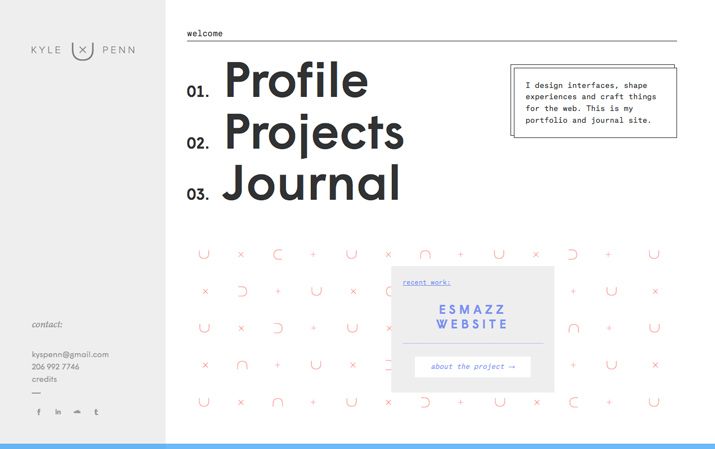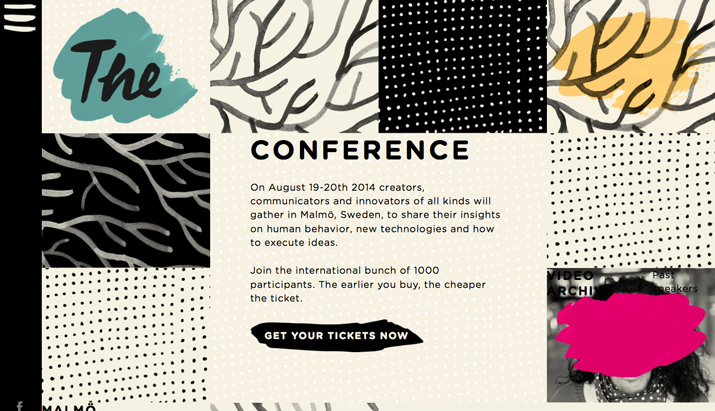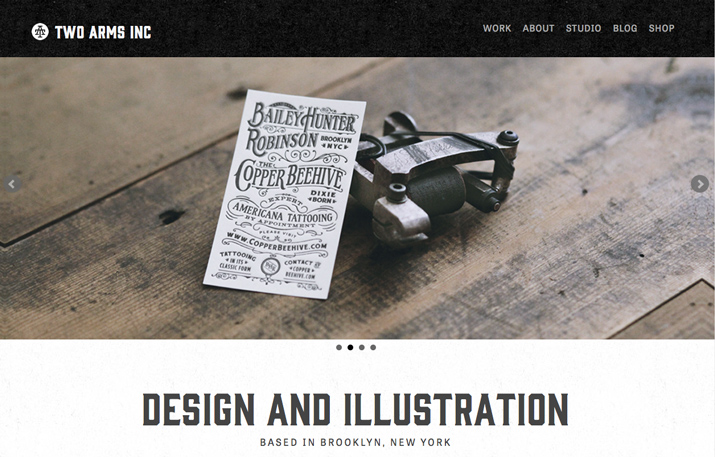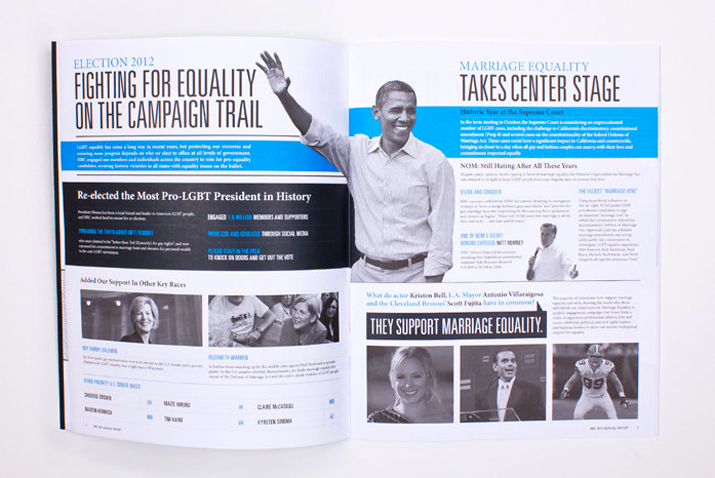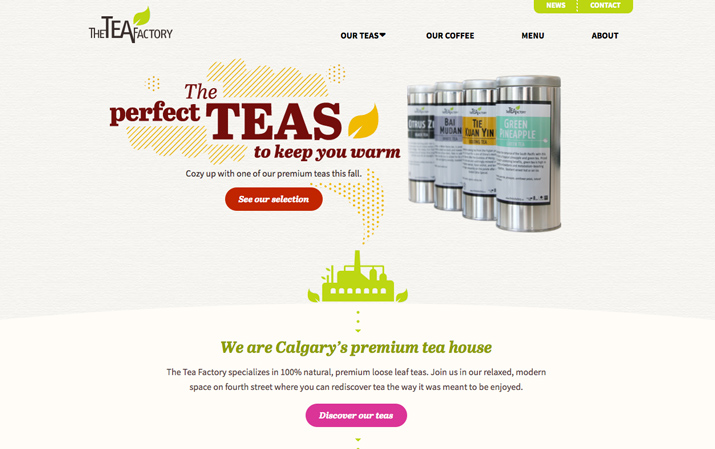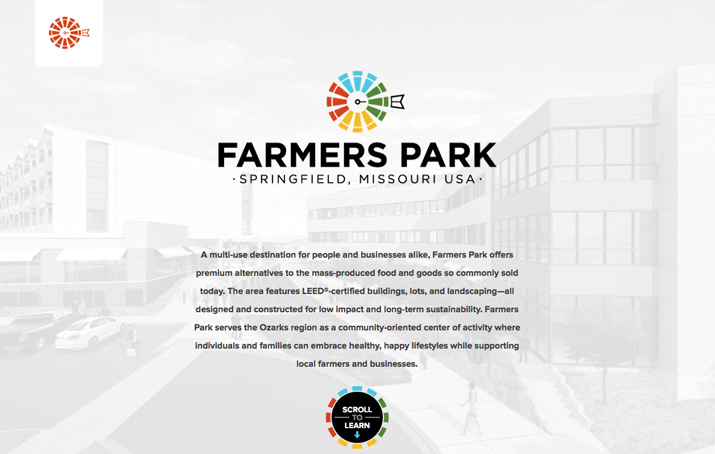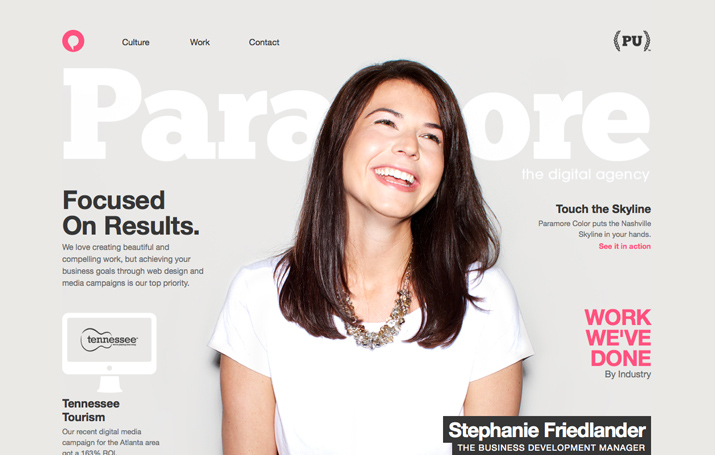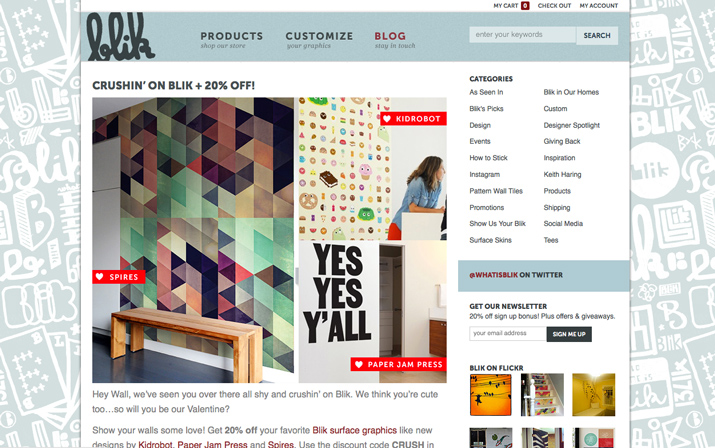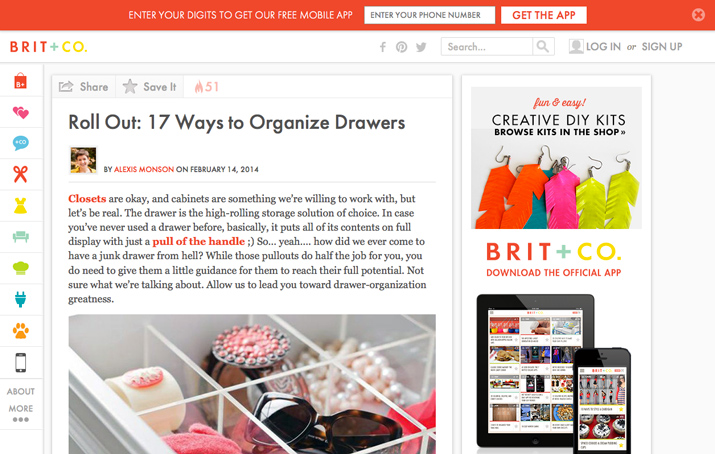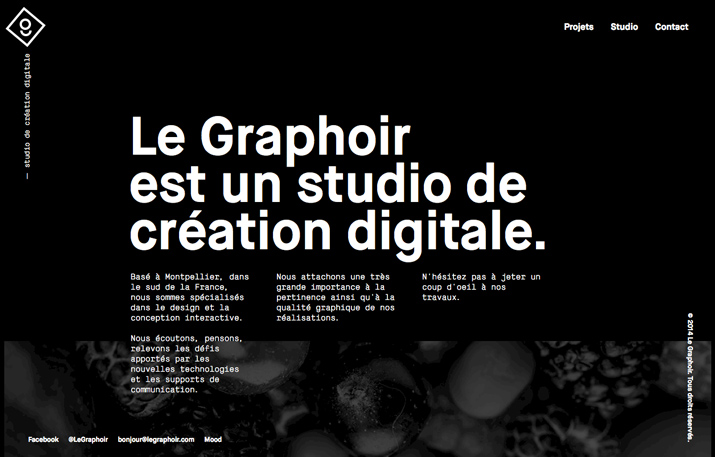
Diseño web: Crea jerarquía visual en tus páginas web usando tipografía
La jerarquía visual es un elemento visual importante en cualquier proyecto de diseño web. Dice a las personas dónde mirar y qué cosas en la pantalla o material impreso son las más importantes. La jerarquía da a los lectores un sentido de cómo leer material, desde el inicio hasta el final, usando pistas visuales.
Aunque puedes crear jerarquía visual usando diferentes herramientas, hoy veremos formas de crear estructuras solo usando tipografía.
Por qué la jerarquía es importante
La jerarquía de fuentes organiza y da orden a los elementos de texto en tu diseño web. Al igual que los desarrolladores y diseñadores web usan etiquetas para encabezados h1, h2 y h3, entre otros para organizar la importancia del texto, la jerarquía visual usa pistas visuales. Además, la jerarquía visual ayuda al lector a escanear el texto, leyendo pedazos de textos de forma más rápida en piezas que lucen similar.
Por lo general, los lectores occidentales empiezan de la parte superior izquierda y hacia la derecha y luego hacia abajo. Las letras están organizadas para imitar este comportamiento. Sin embargo, ¿qué sucede cuando el texto más grande y en negrita se encuentra a mitad de la página web? Generalmente, el lector empezaría por ahí y luego iría la parte superior y continuar con la lectura normal.
La jerarquía es importante porque permite que el diseñador determine lo que alguien leerá primero, segundo y así sucesivamente. Debido a esto, el diseñador puede crear fuentes de una forma en que él o ella sepa qué información puede ser recibida y en qué orden.
Crear jerarquía es importante para los diseñadores, pero estoy es igual de importante para los lectores. Una jerarquía visual buena nos dice lo que es importante porque facilita la lectura. Por ejemplo, sabes que el encabezado es lo más importante (o lo que llama la atención) de la historia porque es lo más grande, seguido de los subencabezados y luego el cuerpo del texto. Para propósitos de legibilidad, puedes leer el texto grande y tener una idea si el artículo será interesantes antes de invertir mucho tiempo en el contenido.
Cómo crear jerarquía
No existe una solución simple para crear jerarquía visual usando texto. Esto puede crearse con tamaño, peso, color, textura, opciones de fuentes y combinaciones, orientación y espacio o una combinación es todo lo mencionado.
Tamaño
Una de las formas más sencillas de establecer jerarquía con tipografía es a través del tamaño. Los lectores, con frecuencia, ver la tipografía más grande primero y empiezan a leer desde ahí.
Con relación al tamaño, la escala es muy importante. Para crear una jerarquía diferente, los tamaños deben tener una variación diferente en relación con las otras fuentes de la página. Lo que debes considerar es que las diferentes fuentes crean escalas diferentes. así que cambiar el tamaño de punto puede no ser diferente; necesitas mirar cómo las fuentes funcionan juntas para asegurar el tamaño y escala apropiados.
Entonces, ¿cómo empiezas a crear el tamaño y escala adecuados para un proyecto? Empieza con el texto principal y parte desde ahí. En cuanto a elementos de texto que son usados para llamar la atención, sé atrevido:
Aquí tienes algunos porcentajes que pueden ayudarte:
- Texto principal (14 puntos)
- Encabezados principales 250 % más que el cuerpo de texto (35 puntos)
- Encabezados secundarios: 175 % más que el cuerpo de texto (25 puntos)
- Elementos de navegación: 165 % más que el cuerpo de texto (25 puntos)
- Menú o menús secundarios: 140 % más que el cuerpo de texto (20 puntos)
Fuentes
Después del tamaño, las fuentes son el elementos más usado en términos de creación de jerarquía tipográfica. La clave es tener contraste entre las fuentes. Esta es la razón por qué los diseñadores seleccionan una fuente serif y otra sans serif para un proyecto.
Para tener las mejores combinaciones, busca fuentes que sean diferentes en peso la tener un tono o sensación similar. Por ejemplo, si estás usando fuentes redondas, usa letras con formas similares en las O. Opta por fuentes con pesos similares si lo estilos se usarán en línea con otros a lo largo del proyecto.
Peso
El grosor de los brochazos en la fuente que elijas para un proyecto también puede crear jerarquía. Mientras más gruesa la fuente, más llamativa y grande aparece. Las fuentes condensadas y livianas pueden parecer más pequeñas de lo que realmente son. Las fuentes muy en negrita pueden parecer más grande de lo que son.
Cuán grande o pequeño parecer ser una fuente es relativo a las otras fuentes usadas en un proyecto. Juntar fuentes gruesas y delgadas crea una sensación de jerarquía.
Color
Usar color también añade énfasis y peso a la fuente. Piensa en algunas de las reglas de color que aprendiste de pequeño: colores cálidos (rojos, amarillos, marrones) tienen más protagonismo mientras que los colores fríos (azules, morados, grises) se desvanecen.
Al usar colores para establecer jerarquía, considera los tonos usados para el primer plano, la fuente y fondo. El contraste de color también juega un papel importante. Los colores más saturados y brillantes, con frecuencia, resaltan en la pantalla a comparación de los tonos más apagados.
Orientación
Cómo el texto aparece en el diseño con relación a otros textos puede impactar la jerarquía general. Por lo general, el texto está orientado de forma horizontal en una línea derecha a lo largo de la pantalla. Sin embargo, ¿qué sucede con el texto vertical?
Este cambio de orientación lleva la atención a aquellas palabras o bloque de texto, haciéndolos aparecer como el elemento más importante. Inclinar, modificar o alterar la forma del texto puede lograr el mismo efecto.
Espacio
Aunque el espacio puede hacer que el texto parezca más grande y más legible, la falta de este logra el efecto contrario. Usa el espacio para tu beneficio al crear una sensación de jerarquía.
Considera el espacio que usas entre líneas de texto. Piensa en el espaciado para las fuentes más grandes. Piensa en la relación entre las letras y el borde de la plantilla. Piensa en las relaciones entre las fuentes de diferentes tamaños, estilo y colores.
Cada espacio puede impactar en tu escala jerárquica. Mantén fuentes similares agrupadas juntas con menos espacio que los elementos que no están relacionados. Diseña tu espacio para que el texto encaje en tu diseño web de una forma agradable. Los elementos de texto brillantes y más grandes, por lo general, necesitan más espacio que los bloques de texto más pequeños y sencillos.
Textura
La textura es un concepto vago en términos de espacio. No, no estamos hablando de colocar un textura dentro de las letras, sino de crear un patrón de textura con la forma en que las letras y palabras descansan en la página web.
Dentro de bloques de texto, puedes conseguir un patrón texturizado. Para establecer más jerarquía, quiebra el patrón. Puedes lograr esto usando una de las herramientas ya mencionadas o cambiando algo tan simple como la alineación de un bloque de texto.
Este cambio en la textura general de texto puede tener un impacto real en la forma cómo el texto es percibido. Sé cuidadoso al realizar demasiados cambios en la textura porque pueden distraer la vista.
3 (o 4) niveles de fuente
Aunque algunos proyectos demandan jerarquías complejas, la mayoría de páginas web pueden tener éxito con tres niveles de jerarquía tipográfica. Estos niveles van el orden primario, secundario y terciario. Esta escala no incluye banners o tipografía del diseño de logo. Estos últimos podrían ser considerados como un cuarto nivel de tipografía (nivel de arte).
Primer nivel: Con frecuencia, es la tipografía en la página web con el mayor peso visual, como los encabezados principales o citas. Su propósito es llamar la atención de los usuarios el diseño web en general.
Segundo nivel: Es todo el nivel a excepción del contenido principal. Esto puede incluir descripciones, subencabezados o elementos de navegación o estáticos.
Tercer nivel: Es el cuerpo de cuerpo. Debes recordar algo con este nivel: debe ser legible.
Nivel de arte: Es la fuente usada como elemento gráfico. No está considerado como fuente porque es mucho más visual. Esto incluye banners y diseños de logos, imágenes compuestas por letras o cualquier otro adorno con tipografía pesada. Por lo general, las fuentes artísticas consisten de una sola letra o palabra y no es parte de lo que las personas esperan leer en el diseño web general.
Conclusión
Organizar fuentes puede ser divertido, pero desafiante. Al combinar técnicas y diferentes efectos y estilos de fuentes pueden lograr un buen flujo de texto en tu página web.
Recuerda considerar las relaciones entre tamaño, peso, color, textura y combinaciones de los mismos, orientación y espacio al crear un bosquejo. Piensa cómo las personas leen y digieren información al usar estas técnicas para que el contenido luzca organizado y fluya en un formato lógico.